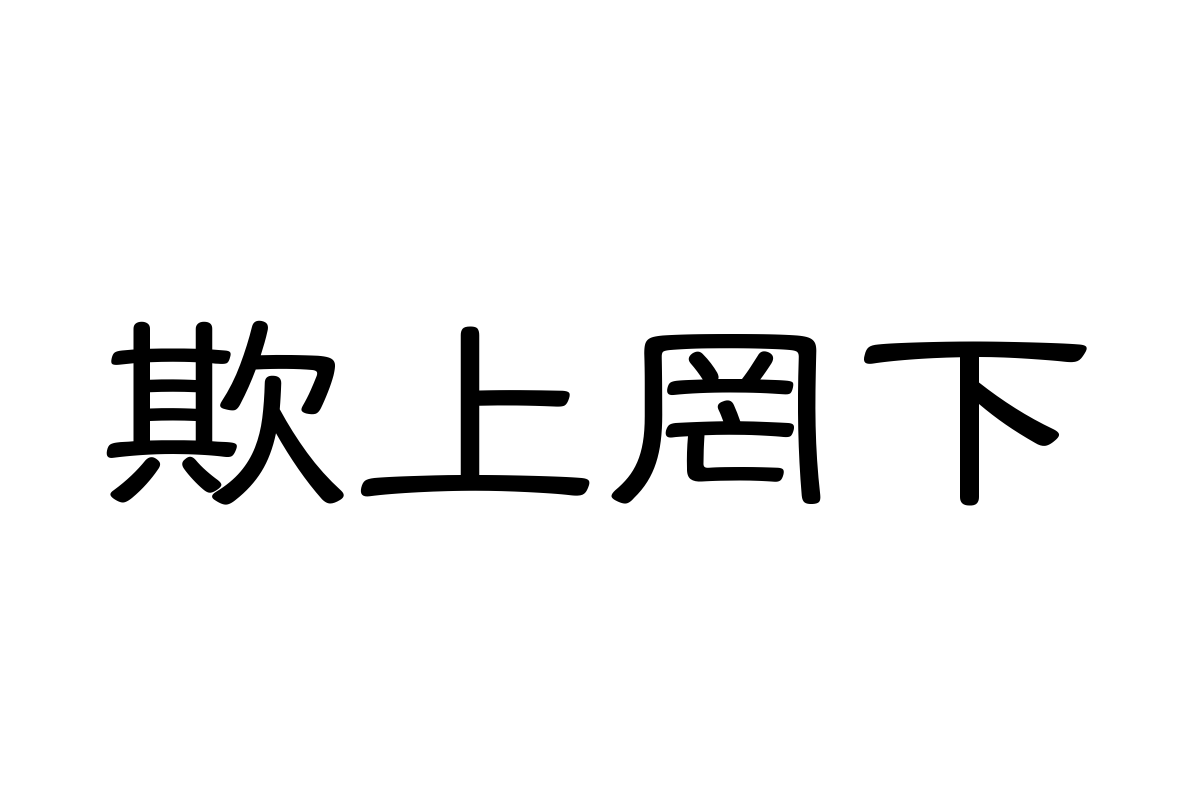
汉仪玉筋隶55是一款由汉仪公司推出的字体,具有独特的风格和特点。这款字体采用了传统的隶书笔法,笔画流畅、有力,线条粗细适中,既有力度又不失柔美。同时,字体结构规整,字形端正,给人一种庄重、大气的感觉。
汉仪玉筋隶55适用于各种需要展示传统文化气息的场合,如广告设计、产品包装、书籍封面等。它不仅能够提升作品的整体视觉效果,还能够传递出一种古典雅致的氛围。